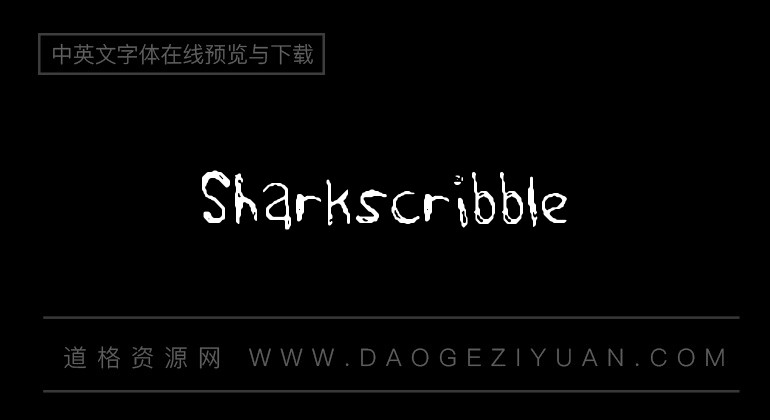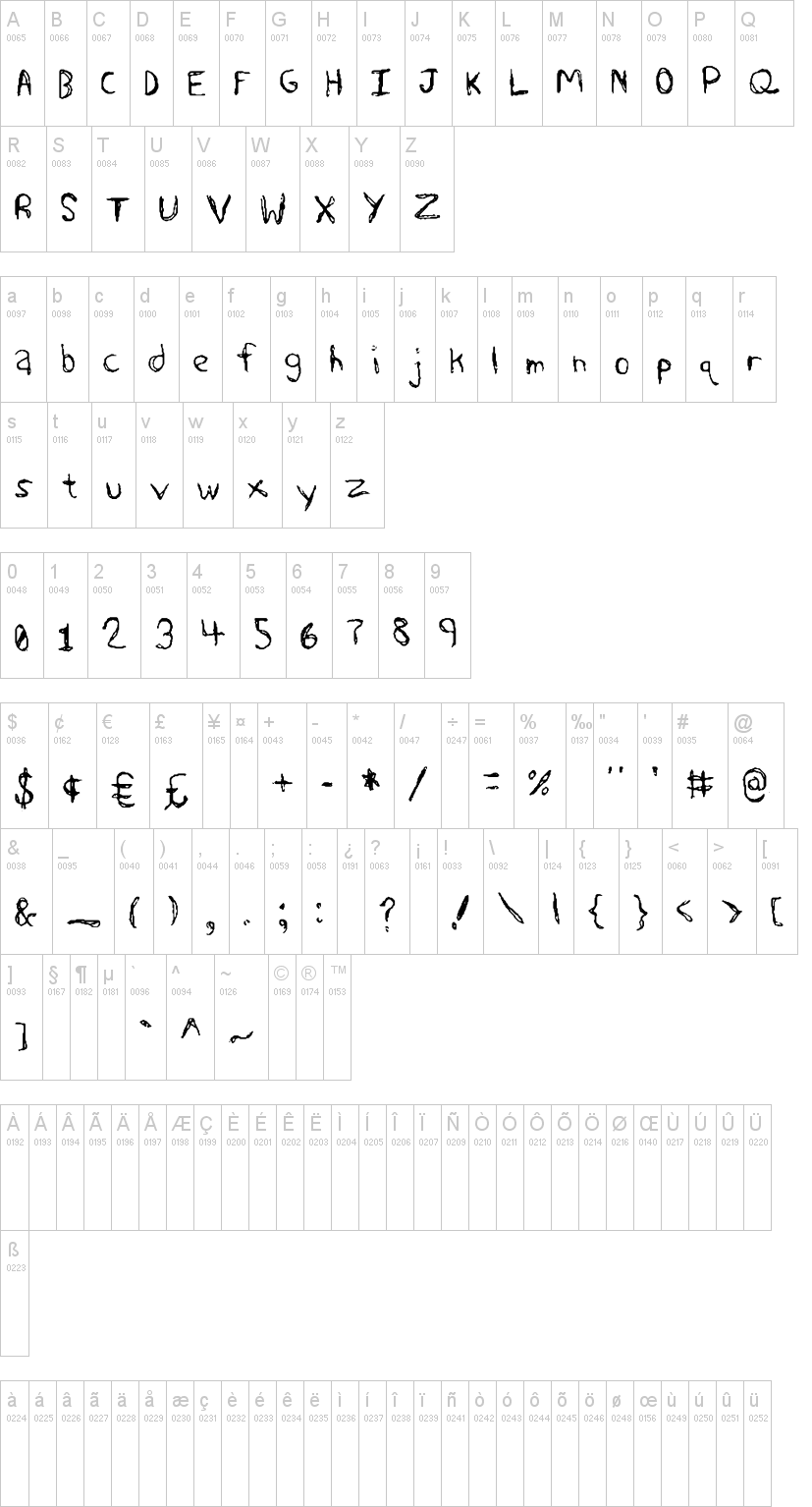
Sharkscribble 是一款由英国设计师Robbie Manson创作的独特字体,它以海豚的涂鸦为灵感来源。这款字体可以让您的文字更加有趣、有趣、有趣,而且它的设计也充满了动感和活力。Sharkscribble 字体的字符特点是曲线状的笔画,它的字体风格灵感来源于海豚的涂鸦,可以让您的文字更加有趣、有趣、有趣,而且它的设计也充满了动感和活力。它可以用于任何文本,例如标题、标签、广告、商标等,可以为您的设计增添活力和趣味性。内容介绍
Sharkscribble是一款非常不错的手写艺术字体,具有很好的视觉感,适合于文化类的宣传设计、商业类品牌的广告和产品包装设计以及个性化文字排版等较多场景。